2022년 WordPress 사이트를 위한 최고의 Google 글꼴
게시 됨: 2020-11-27웹 사이트의 디자인뿐만 아니라 사용 중인 웹 글꼴도 중요합니다. 콘텐츠는 웹사이트에서 가장 중요한 것입니다. 사이트에서 콘텐츠를 표시하는 방법은 품질만큼 중요합니다. 사용하는 글꼴은 방문자가 웹사이트 콘텐츠를 경험하는 방식을 결정합니다. 따라서 웹 콘텐츠에 적합한 글꼴을 선택하는 것은 항상 중요한 결정입니다. 이 기사에서는 2022년에 사용해야 하는 WordPress 사이트에 가장 적합한 Google 글꼴에 대해 설명합니다.
타이포그래피의 중요성
이 문구를 들어보셨을 것입니다 - 콘텐츠가 왕입니다. 그리고 그것은 어딘가에 사실입니다. 귀하의 사이트에 고품질 콘텐츠가 포함되어 있으면 적절한 청중을 끌어들이고 검색 엔진 순위를 높이는 데 도움이 됩니다. 사람들이 웹사이트를 방문하는 주된 이유는 검색하는 정보를 찾기 위함입니다. 웹사이트를 아무리 잘 디자인하더라도 양질의 콘텐츠가 포함되어 있지 않으면 사람들은 결코 좋아하지 않을 것입니다. 콘텐츠의 품질도 중요하지만 타이포그래피의 중요성을 간과할 수 없습니다. 사이트의 콘텐츠는 매우 중요하며 사이트에 콘텐츠를 표시하는 방식도 똑같이 중요합니다.
타이포그래피는 기본적으로 콘텐츠가 사이트에 표시되는 방식입니다. 그리고 올바른 타이포그래피 선택은 타겟 청중을 끌어들이는 데 매우 중요합니다. 타이포그래피는 글꼴, 크기, 색상, 레이아웃, 정렬 등에 관한 모든 것입니다. 그리고 글꼴은 아마도 타이포그래피의 가장 중요한 부분일 것입니다. 웹 콘텐츠에 가치를 더합니다. 좋은 글꼴은 독자가 텍스트의 정보를 이해하는 데 도움이 되며 사이트를 보다 전문적으로 보이게 합니다.
게다가 콘텐츠를 매력적으로 만들고 사이트의 가독성을 높입니다. 사용할 수 있는 글꼴은 수천 가지이며 Google 글꼴 을 적극 권장합니다. 상업용 및 개인용으로 무료입니다. Google 글꼴 라이브러리를 사용하면 자신의 디자인 요구 사항에 따라 다양한 글꼴을 쉽게 선택하고 활용할 수 있습니다. 이 기사에서 권장하는 최고의 Google 글꼴을 사용하면 웹 페이지를 더 빠르게 실행할 수 있습니다.
WordPress용 최고의 Google 글꼴
Google 글꼴 라이브러리 에는 1000개 이상의 Google 글꼴이 있습니다. 따라서 WordPress 사이트에 가장 적합한 Google 글꼴을 선택하는 것은 약간 어려울 수 있습니다. 하지만 걱정하지 마세요! 1000개 이상의 글꼴 중에서 우리는 귀하의 WordPress 사이트에 가장 적합한 7가지 Google 글꼴을 선택했습니다. Roboto Google Font , Open Sans Google Font , Merriweather Google Font , Lato Google Font , Source Sans Pro Google Font , Noto Sans Google Font 및 오스왈드 구글 폰트 .
#1 – Roboto Google 글꼴
- 범주: 산세리프체
- 분류: 네오 그로테스크
- 디자이너: 크리스찬 로버트슨
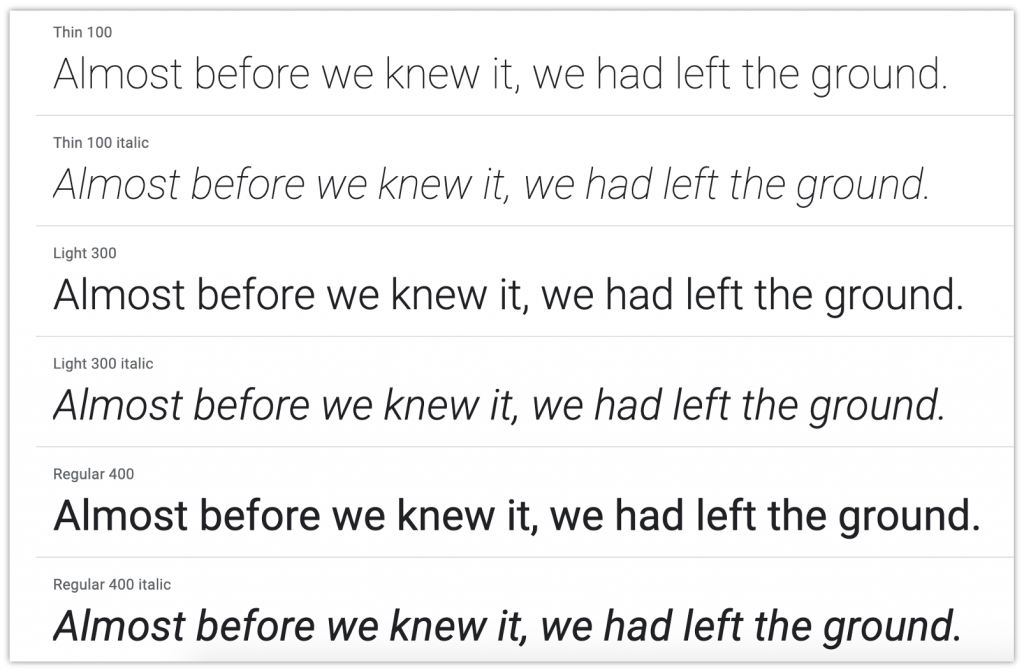
원래 Android 운영 체제용 시스템 글꼴로 개발된 Roboto 는 Google에서 제공하는 오픈 소스 네오 그로테스크한 산세리프체입니다. 12가지 스타일로 제공되는 가장 인기 있고 최고의 Google 글꼴 중 하나입니다. Roboto는 대부분 기하학적 형태의 기계 골격을 특징으로 합니다. 동시에 친근하고 개방적인 곡선을 지원합니다. 다른 Google 글꼴과 달리 Roboto는 문자 형식을 손상시키지 않고 문자가 자연스러운 너비를 사용할 수 있도록 합니다. Roboto Google 글꼴을 사용하면 웹 콘텐츠의 가독성을 쉽게 높일 수 있습니다.
#2 – Sans Google 글꼴 열기
- 범주: 산세리프체
- 분류: 휴머니스트
- 디자이너: 스티브 매테슨
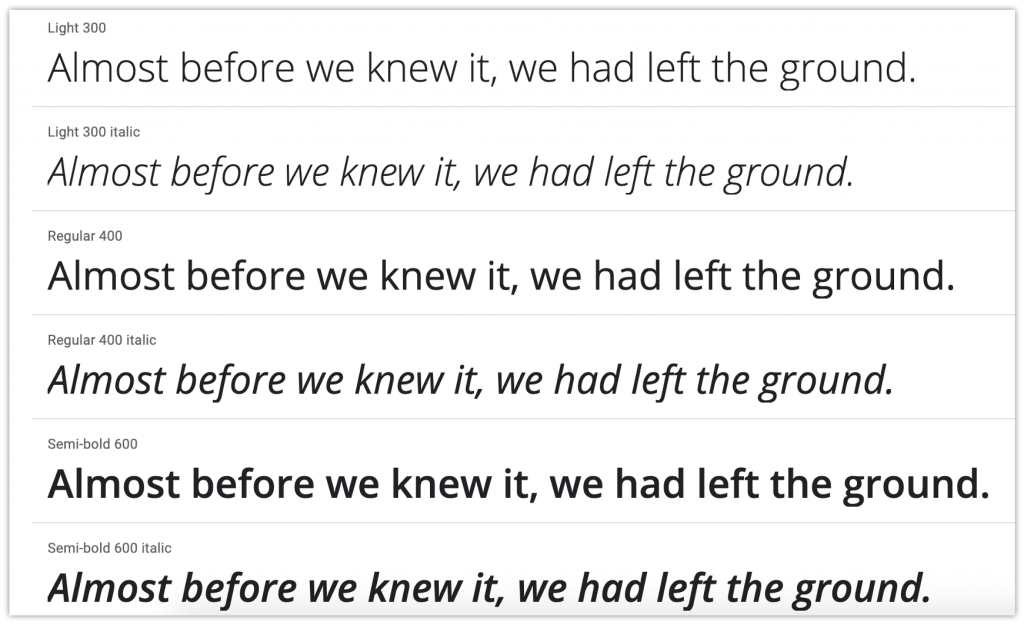
Open Sans 는 WordPress 사이트에서 사용해야 하는 또 다른 인기 있는 Google 글꼴입니다. Google 글꼴 라이브러리에서 두 번째로 많이 제공되는 글꼴입니다. Open Sans는 Android 운영 체제용으로 설계되었지만 다른 sans-serif 서체보다 약간 넓습니다. 10가지 스타일로 제공되는 휴머니스트 산세리프체입니다. 개방형 sans 서체는 작은 크기에서도 화면에서 매우 가독성이 높습니다. 인쇄, 웹 및 모바일 인터페이스에 최적화되어 있습니다. Open Sans Google 글꼴을 사용하면 텍스트에 중립적이면서도 친근한 느낌을 줄 수 있습니다.
#3 – Merriweather Google 글꼴
- 범주: 산세리프체
- 분류: 반 응축
- 디자이너: 소킨 타입
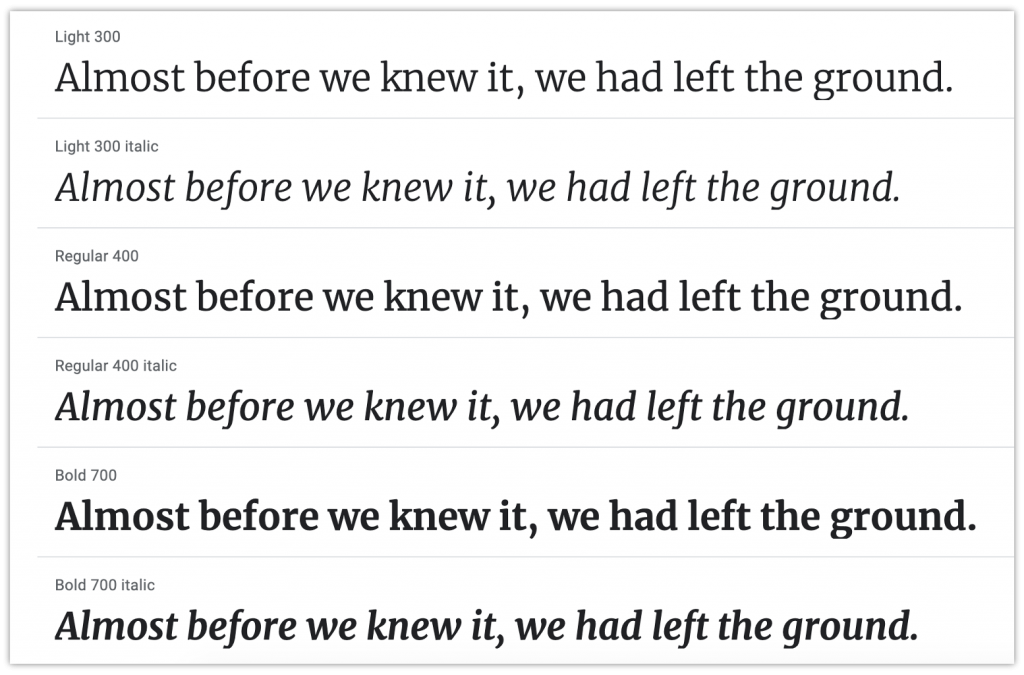
화면에서 읽기 좋은 Google 글꼴을 찾고 있다면 글꼴 라이브러리에서 사용할 수 있는 최고의 Google 글꼴 중 하나인 Merriweather 사용을 반드시 고려해야 합니다. 화면용으로 특별히 설계된 강력한 텍스트 유형 제품군입니다. Merriweather Google 글꼴은 8가지 스타일로 제공됩니다. 그것은 매우 큰 x-높이, 견고한 세리프체, 약간 압축된 글자체, 열린 형태 및 약한 대각선 응력을 특징으로 합니다. Google 글꼴 라이브러리에서 사용할 수 있는 다른 많은 serif 글꼴과 달리 Merriweather에는 Light , Regular , Regular Italic , Bold 및 Heavy 와 같은 완전한 스타일 및 두께 세트가 포함되어 있습니다.
#4 – Lato Google 글꼴
- 범주: 산세리프체
- 분류: 휴머니스트
- 디자이너: Lukasz Dziedzic
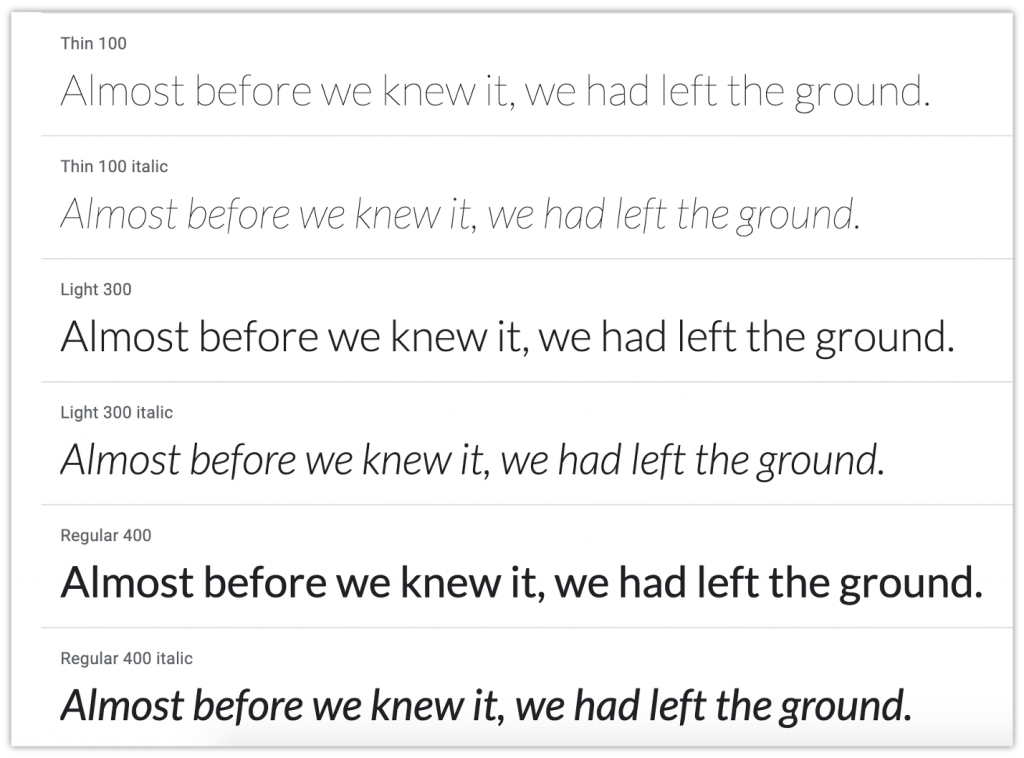
Lato 는 Google에서 제공하는 또 다른 sans-serif 서체이며 10가지 스타일로 제공됩니다. 가장 인기 있고 최고의 Google 글꼴 중 하나인 이 글꼴은 전 세계 960만 개 이상의 웹사이트에서 사용됩니다. Lato는 원래 기업용으로 설계되었지만 다양한 물리적 출판물에 사용되었습니다. 글자의 반원형 디테일이 있는 이 Google 글꼴은 텍스트에 따뜻한 느낌을 줍니다. 게다가 Lato의 강력한 구조는 텍스트의 안정성과 진지함을 제공합니다. 이것이 글꼴 디자이너 Lukasz Dziedzic이 Lato를 "진지하지만 친근한" Google 글꼴로 설명하는 이유입니다. 키릴 자모, 그리스어 및 IPA와 함께 모든 라틴 알파벳을 지원합니다.
#5 – 소스 Sans Pro Google 글꼴
- 범주: 산세리프체
- 분류: 그로테스크한 산세리프; 휴머니스트 산세리프체
- 디자이너: 폴 D. 헌트
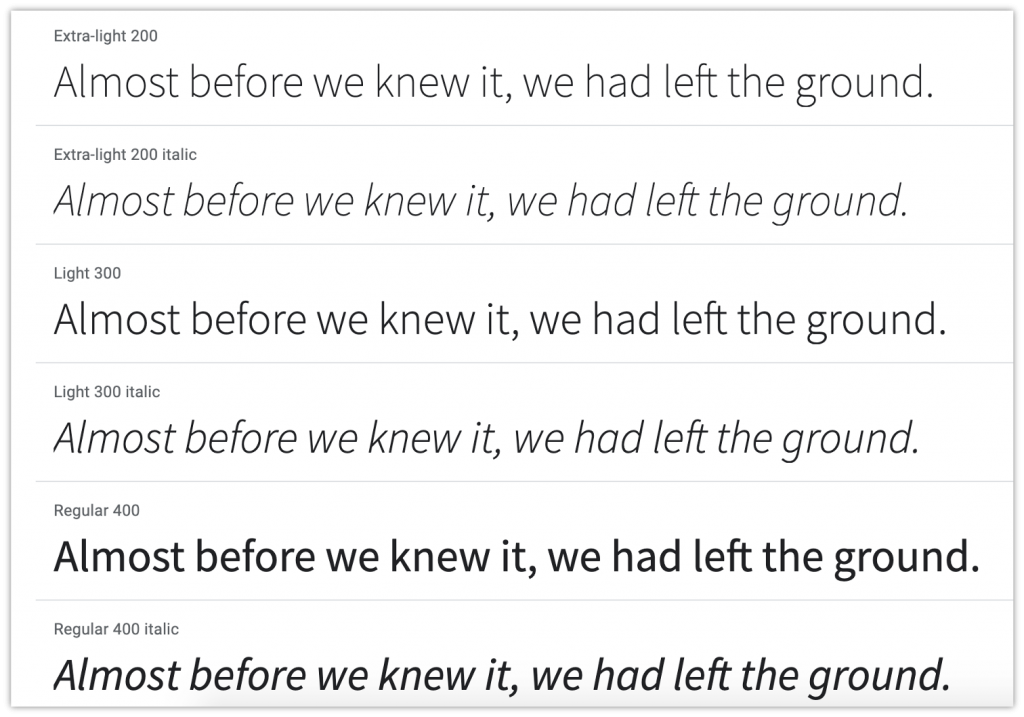
Source Sans Pro 는 Adobe의 첫 번째 오픈 소스 글꼴 모음입니다. 12가지 스타일로 제공되는 현대적인 Google 글꼴입니다. Source Sans Pro는 세계 최고의 Google 글꼴 중 하나로 간주됩니다. 작은 크기에서도 사용자 인터페이스에서 멋지게 보입니다. Source Sans Pro Google 글꼴은 6가지 두께와 12가지 스타일로 제공되어 매우 다양합니다. 개인 및 상업적 사용은 무료입니다. Source Sans Pro는 라틴어 스크립트에 대한 광범위한 언어 지원을 제공합니다. 그것은 서유럽 및 동유럽 언어, 병음 로마자 표기법, 베트남어 및 나바호어를 지원합니다.
#6 - 오스왈드 구글 폰트
- 범주: 산세리프체
- 분류: 대체 고딕
- 디자이너: Vernon Adams, Kalapi Gajjar, Alexei Vanyashin
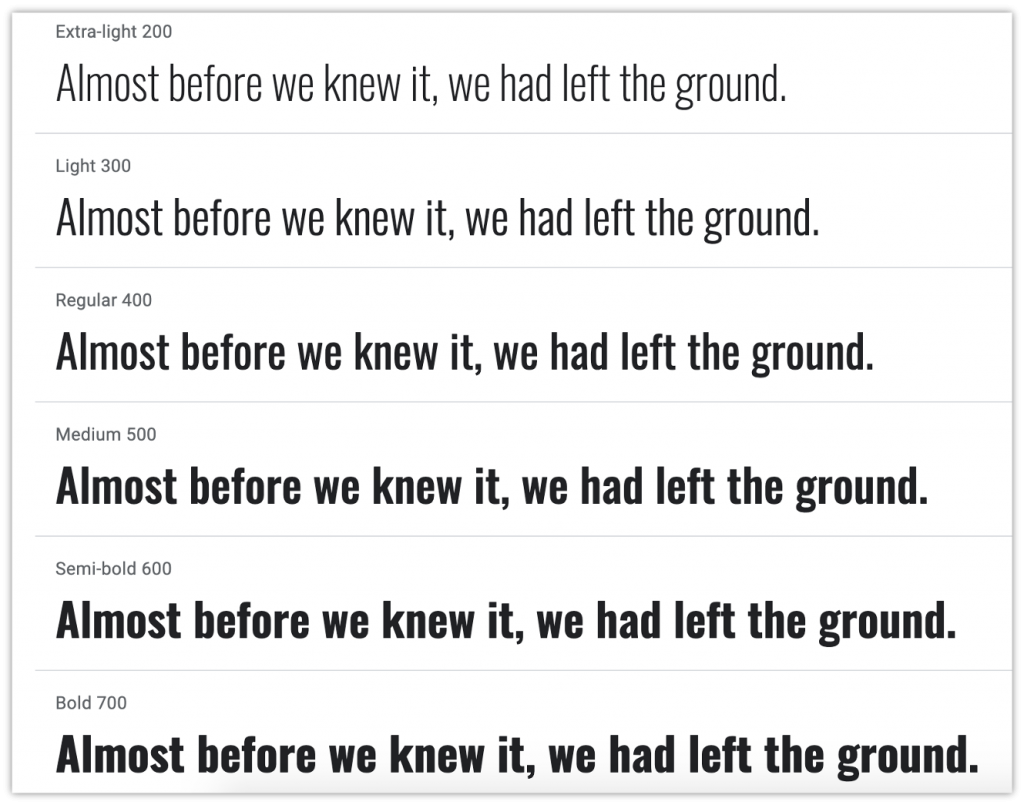
Oswald 는 Google 글꼴 라이브러리에서 사용할 수 있는 또 다른 인기 있는 산세리프 글꼴입니다. 이 구글 글꼴은 PC, 노트북, 태블릿, 모바일 등 모든 기기의 모든 웹 브라우저에서 인터넷을 통해 자유롭게 사용할 수 있도록 설계되었습니다. Oswald는 모든 라틴 언어와 키릴 문자를 사용하는 언어를 지원합니다. Oswald Google 글꼴을 사용하면 웹 콘텐츠를 더 아름답고 빠르게 만들 수 있습니다.
#7 – Noto Sans Google 글꼴
- 범주: 산세리프체
- 분류: 산세리프체(인본주의자); 세리프(과도기); 비라틴어
- 디자이너: 구글
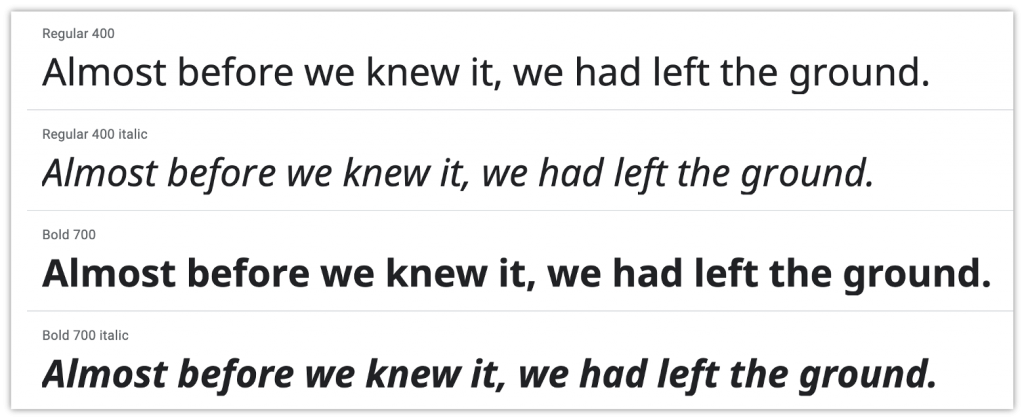
Noto Sans 는 전 세계 최대의 언어를 지원하는 것을 목표로 하는 Noto 글꼴 패밀리의 일부입니다. Noto 글꼴은 다양한 언어에서 조화롭게 보이도록 설계되었습니다. 이 인기 있는 Google 글꼴은 Regular , Bold , Italic 및 Bold Italic 의 4가지 스타일로 제공됩니다. Noto Sans를 사용하면 호환되는 높이와 획 두께로 여러 플랫폼에서 텍스트를 더 아름답게 보이게 할 수 있습니다. Noto 글꼴은 세계에서 가장 인기 있는 웹 글꼴 중 하나이며 Noto Sans는 WordPress 사이트에 가장 적합한 글꼴 옵션 중 하나입니다.
결론
좋은 글꼴은 콘텐츠의 가독성 점수를 높일 수 있습니다. 따라서 웹 사이트에 적합한 글꼴을 선택하는 것은 항상 중요한 결정입니다. Google 글꼴은 훌륭하며 웹에서 매일 수백만 개의 웹사이트에서 사용됩니다. 이 기사에서는 WordPress 사이트에서 사용할 수 있는 최고의 Google 글꼴에 대해 논의했습니다. 아래 댓글 섹션에서 가장 좋아하는 Google 글꼴을 알려주십시오. 당신은 또한 관심이있을 수 있습니다 – 웹 사이트를 개선하는 데 매우 중요한 웹 디자인 팁 .